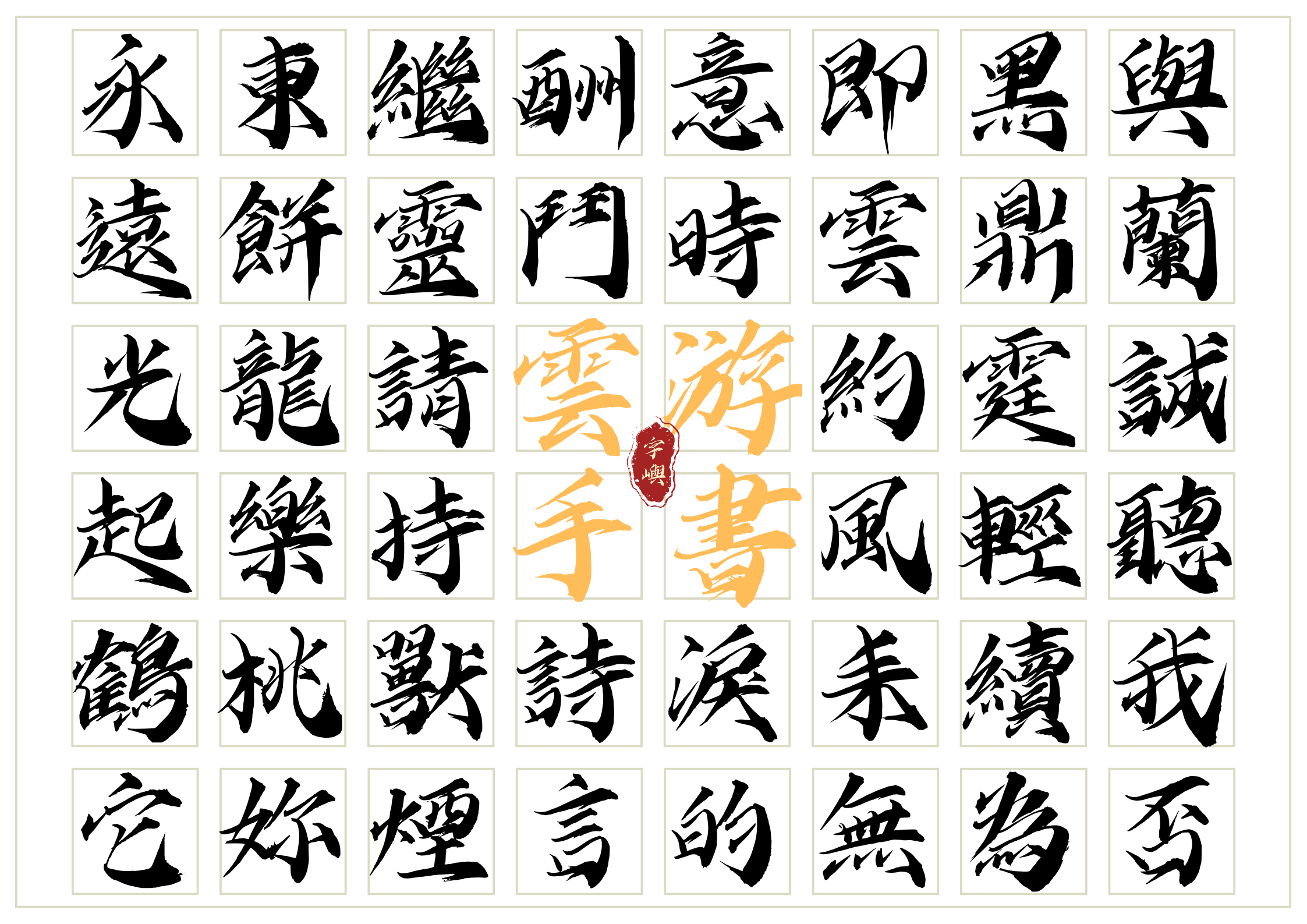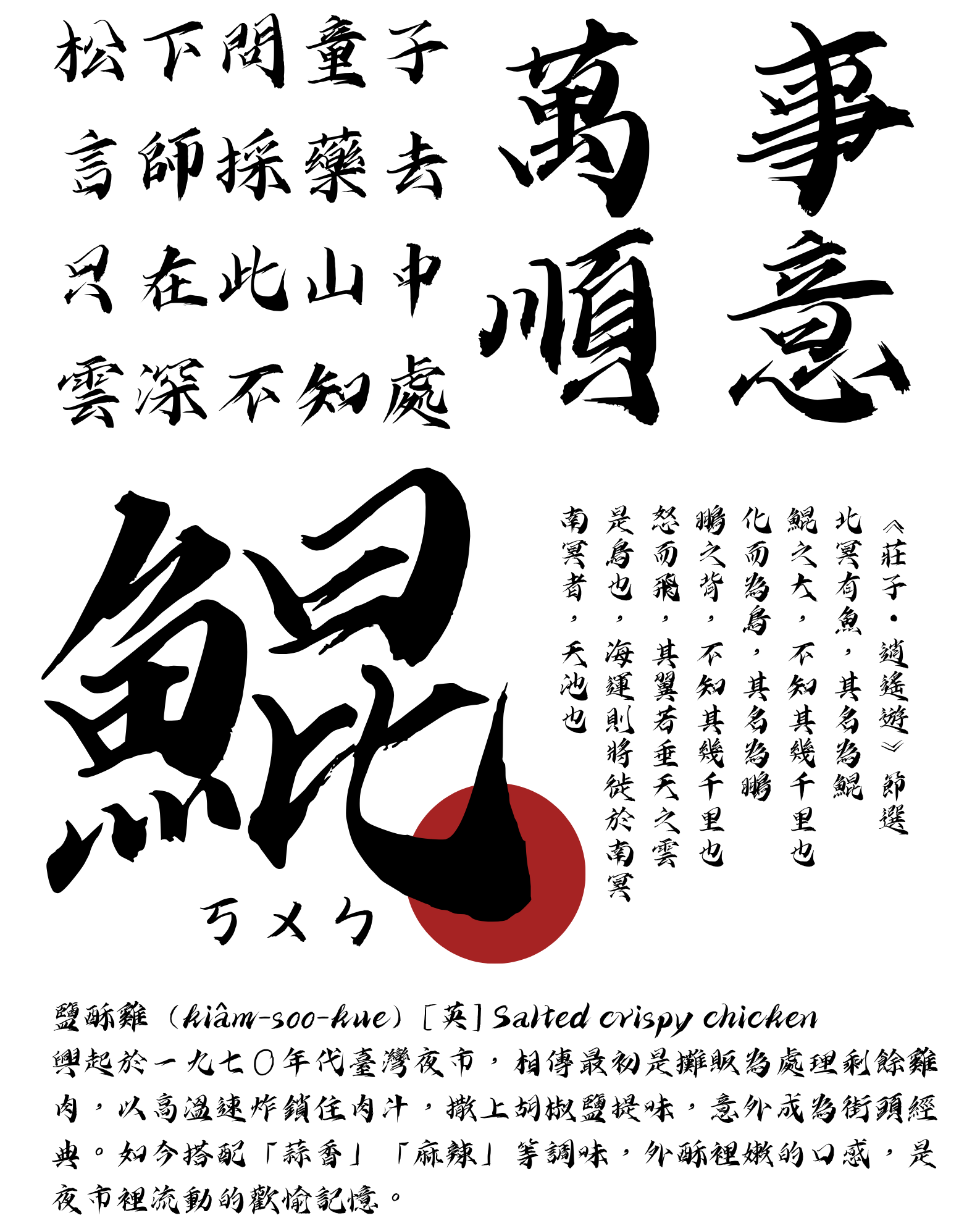
字嶼雲遊手書
字屿云游手书是一款以传统毛笔书写风格为基础打造的创意手书字体。字体在保留毛笔运笔特征的基础上,进一步强化了笔画之间的曲折变化、收放关系以及整体字势的动态表现,使文字呈现出更加鲜明的视觉张力。不同于常规书法字体对传统笔迹的简单模拟,字屿云游手书通过对笔画形态的重新设计,让字体兼具书法韵味与现代设计感,在自然流动的书写气息中展现出独特的东方美学。
从整体字形来看,字屿云游手书具有明显的毛笔书写痕迹。字体采用露锋用笔方式,起收笔变化丰富,笔画之间存在明显的轻重、快慢与方向变化,使每个字都具有较强的运动感。字体结构并非追求规整端正,而是在开合揖让之间寻找平衡,通过局部形变与笔势外拓增强视觉表现力。部分笔画舒展外放,形成飘逸灵动的效果;部分结构收紧凝聚,使字体在自由变化的同时保持稳定的识别度。
在风格表现上,字屿云游手书融合了传统书法中的柔美与力量感。大量曲线笔画强化了文字的流动性,如同云气游走,又带有锋刃般的锐利感,因此整体呈现出“飘逸中带有刚劲”的视觉特点。字体既具有手写书法的自然温度,也具备展示型字体所需要的艺术感染力,适合用于强调情绪表达和文化气质的设计场景。
字屿云游手书以台语常用标准汉字为基础制作,参考 jf7000 字集,包含注音符号、欧文字符、阿拉伯数字以及常用标点符号,总字符数量约 7640 字以上,能够满足日常中文排版与设计需求。字体覆盖范围较为完整,在保持书法风格的同时,也兼顾了实际使用中的字符需求。
在应用场景方面,字屿云游手书适合用于国潮文创、品牌包装、茶饮礼盒、伴手礼设计、出版物封面、影视标题、传统文化海报以及商业视觉设计等领域。其强烈的毛笔质感与东方气息,能够为作品增加传统文化氛围。例如在茶饮包装、中式品牌标识、古风故事书封面、展览海报以及文博类设计中,都能够发挥较好的视觉效果。
总体而言,字屿云游手书是一款兼具传统书法气韵与现代视觉表现力的创意毛笔字体。它通过丰富的笔势变化、灵动的结构关系以及强烈的书写感,将东方书法中的力量与流动感融入数字字体设计之中,适合应用于需要突出文化感、艺术感以及品牌个性的视觉项目。